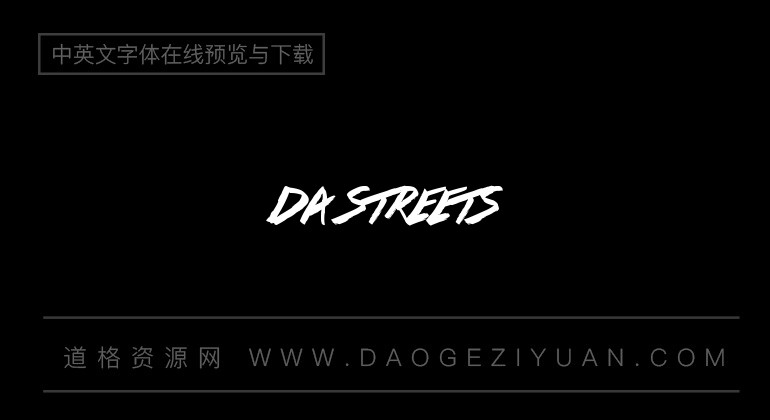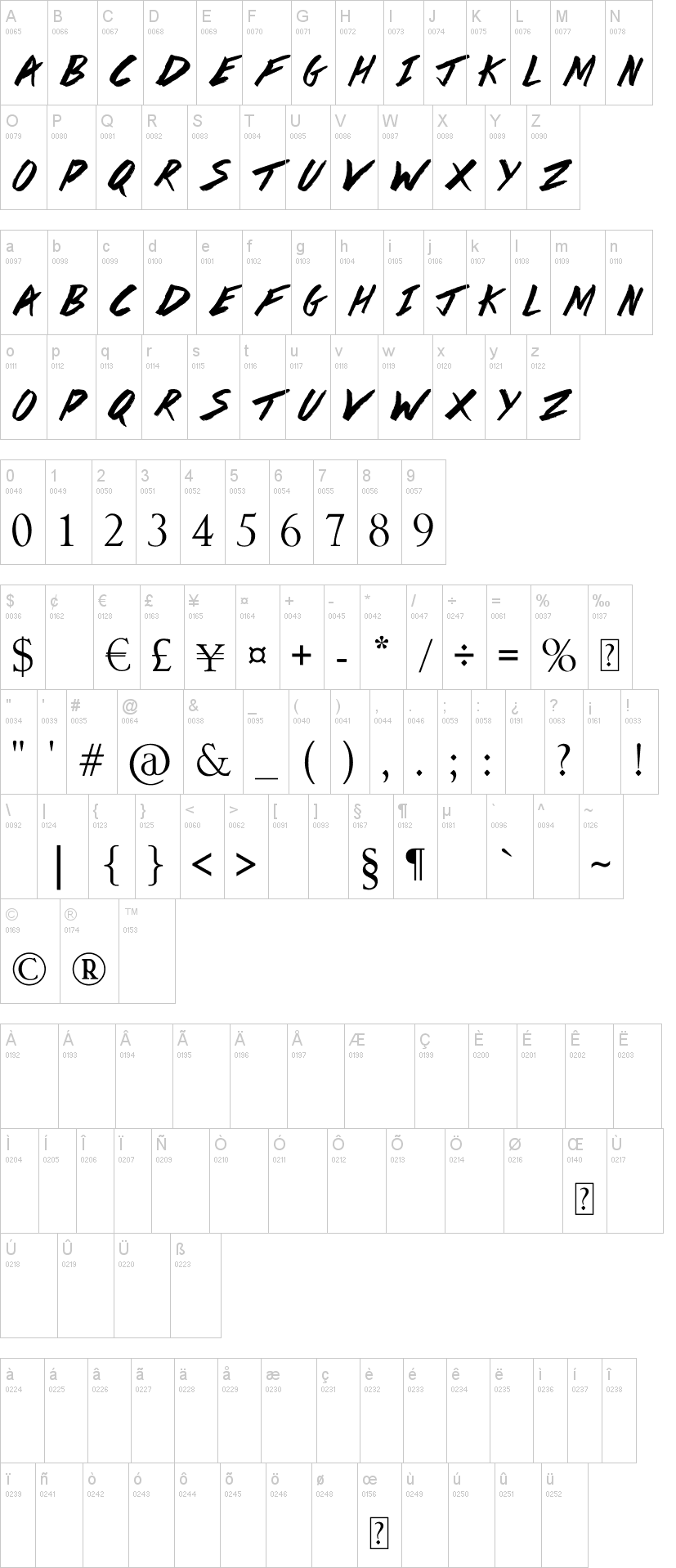
Da Streets 字体是一种涂鸦艺术家和街头文化爱好者经常使用的字体。它的设计灵感来源于城市街头涂鸦和涂鸦艺术的视觉语言,并且结合了许多街头文化的元素和符号。 这种字体通常使用粗体和强烈的线条来表达力量和动态感,同时也注重字母之间的连通性和流畅性,使整个字体看起来更像一个整体。通常使用明亮的颜色和渐变效果来增强其视觉效果,从而更好地表达出街头文化的特点和风格。 由于其富有个性和创意的设计风格,Da Streets 字体在广告设计、海报设计、涂鸦艺术、街头艺术等许多领域都得到了广泛的应用,并受到了越来越多的设计师和艺术家的喜爱。内容介绍
Da Streets是一款非常不错的手写艺术字体,具有很好的视觉感,适合于文化类的宣传设计、商业类品牌的广告和产品包装设计以及个性化文字排版等较多场景。